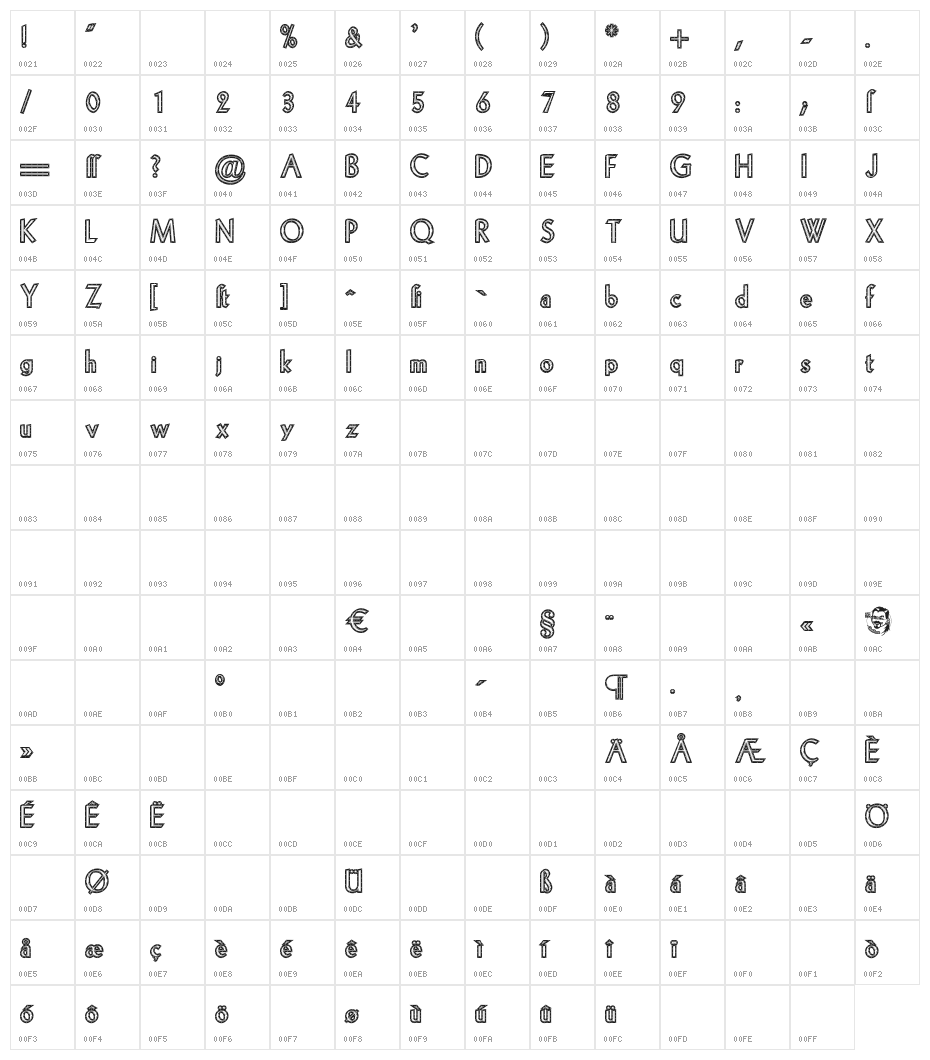
StahlSteelRiveted Font
| Gesamtstil | Industrial, Mechanical |
| Anwendungsfall | Logos, Posters, Branding |
| Vorgeschlagene Projekte | Ideal for industrial-themed designs, posters, logos, and branding that require a strong, mechanical feel. |